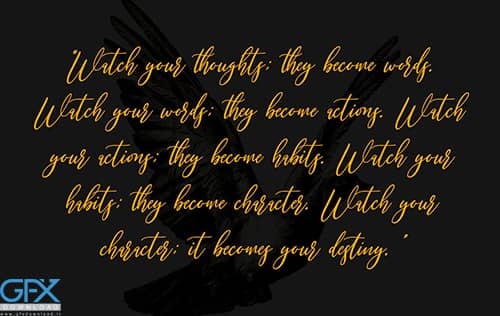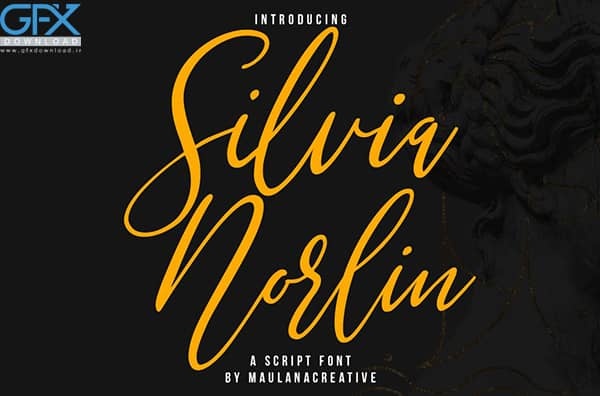
فونت زیبای انگلیسی Silvia Norlin
فونت زیبای انگلیسی خمیده Silvia Norlin
این فونت زیبا یک فونت اسکریپت انگلیسی خمیده و سرگرم کننده با کمی لیگاتور می باشد. استفاده از این فونت کار شما را خلاقانه می کند. فونت Silvia Norlin بیش از 100+ زبان چندزبانه است. این فونت زیبای انگلیسی Silvia Norlin برای طراحی آرم ، شبکه های اجتماعی ، عنوان فیلم ، عنوان کتاب ، یک متن کوتاه حتی یک نامه طولانی و برای قلم متن با sans یا serif مناسب است. شامل فرمت های (OTF) ، (TTF) و (Web Font).